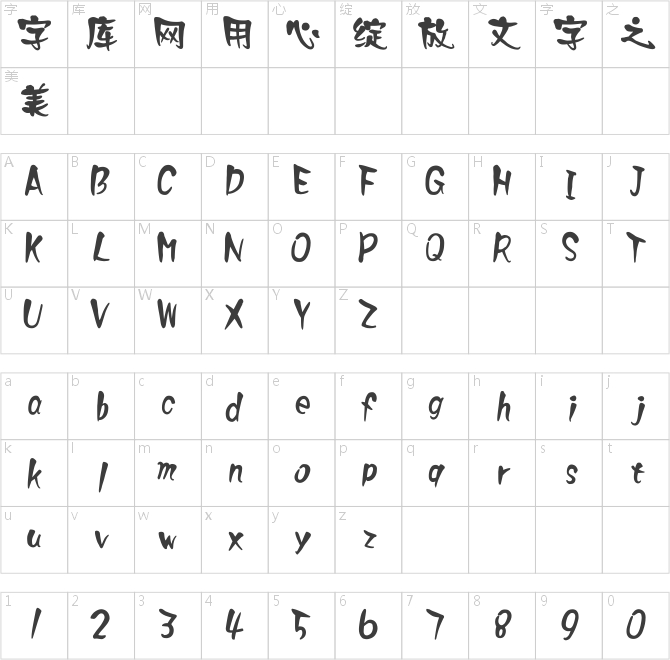
字体名称: 文鼎中特广告体
文鼎中特广告体简繁
文鼎中特广告体简繁介绍
文鼎中特广告体的简体和big5繁体合并成了文鼎中特广告体简繁,该字体向上兼容新版win10。
更新Power TrueType Version 5.0版,和原Power TrueType Version 4.0或Power TrueType Version 4.5版本相比又将原Power TrueType big5的扩展471个外字集的部分没有映射字码点的汉字进行了对号入座,并修复『?』字误映射到『抝』字位置的错误。
文鼎中特广告体简繁字体文鼎大广告体简繁字库是一款让人赏心悦目、百看不厌的中文字体,适合各类广告和产品包装设计应用,字体大小16.32MB,格式为ttf字体,上传用户是伊宁,作者/版权方为文鼎字库
文鼎中特广告体简繁效果图